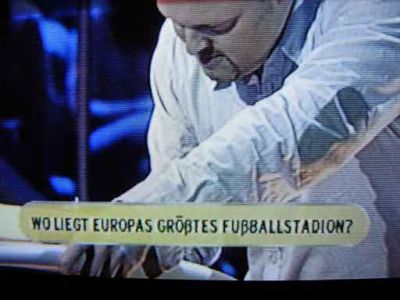
Ach was muss man oft bei diesen Sendern hören oder lesen …
Es regt mich ja schon fast nicht mehr auf …
aber :x :evil::twisted::!:
Harhar! Wir schauen das gleiche Programm
Dafür hab ich wenigstens mit Abstand den schlechteren Fernseher, da fügt sich die typografische Qualität doch viel harmonischer ins Bild.
Georg :D
Was guckt ihr auch für einen Mist … :twisted:
Ihr redet von dem Achter der an Stelle des „B“ verwendet wurde, nicht? :D